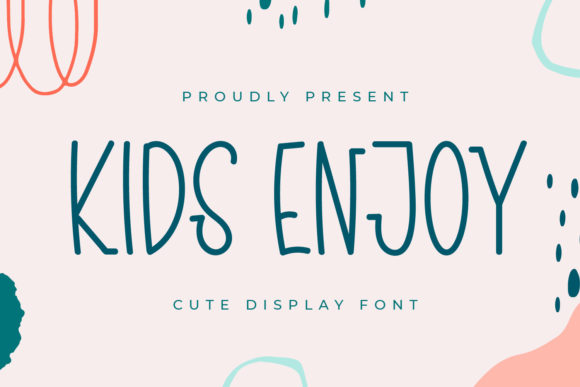
[Creativefabrica] Kids Enjoy Font (2021)
Kids Enjoy - это веселый, дружелюбный и симпатичный шрифт.
Если вы используете его для дизайна, связанного с мультфильмами, детскими играми или просто для любого творения, требующего милого прикосновения, этот шрифт станет отличным выбором!